Zalgo & Glitch Text Generator: So erstellst du gruselige Schriften
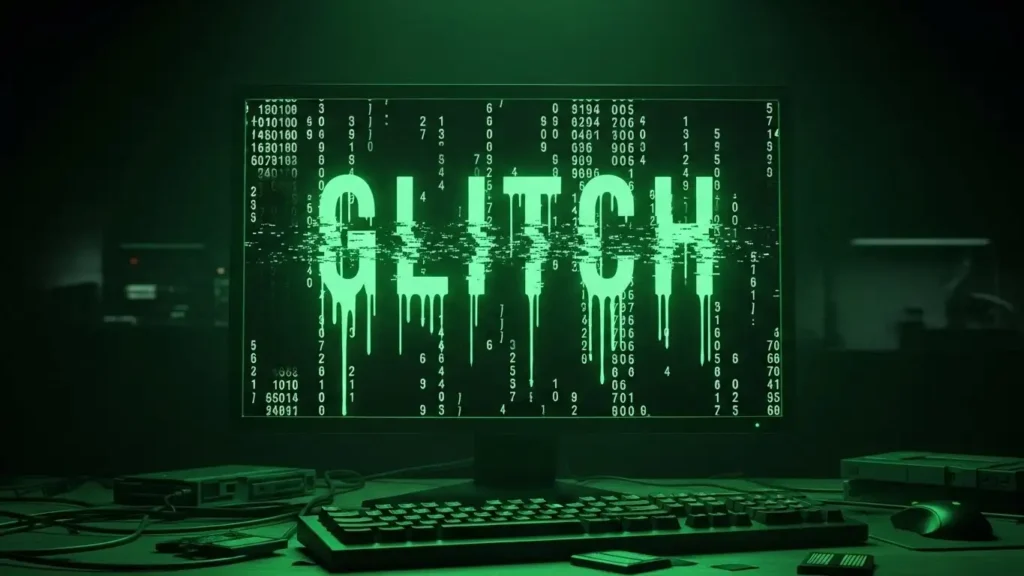
Ein Glitch Text Generator ist das mächtigste Werkzeug, um gewöhnliche Nachrichten in chaotische, visuell verstörende Kunstwerke zu verwandeln, die sofort ins Auge fallen. Hast du dich jemals gefragt, wie andere Nutzer diese seltsamen, “kaputten” Buchstaben erzeugen, die so aussehen, als würde der Bildschirm schmelzen? Das ist kein Fehler in der Matrix. Das ist Absicht.
In der digitalen Welt kämpfen wir alle um Aufmerksamkeit. Ein normaler Text in Arial oder Helvetica geht in der Masse unter. Aber ein Text, der aussieht, als wäre er von einem digitalen Geist besessen? Der fällt auf.
In diesem Artikel zeige ich dir nicht nur, wie du diese Effekte erstellst, sondern erkläre auch die Technik dahinter und worauf du achten musst, damit deine Botschaft lesbar bleibt.
Was ist eigentlich Zalgo Text?
Bevor wir in die Praxis gehen, müssen wir verstehen, was wir hier eigentlich tun. Zalgo Text, oft auch als “Glitch Text” oder “Scary Text” bezeichnet, stammt ursprünglich aus der Internet-Kultur der frühen 2000er Jahre. Der Name bezieht sich auf eine Internet-Legende (Creepypasta) über eine Entität namens “Zalgo”, die Wahnsinn und Zerstörung bringt.
Visuell wird dies durch Text dargestellt, der über die normalen Zeilenabstände hinauswuchert. Es sieht aus, als würde der Text bluten oder zerfließen.
Die Technik: Kombinierende Unicode-Zeichen
Viele glauben, dass man für diesen Effekt programmieren können muss. Das stimmt nicht. Das Geheimnis liegt im Unicode.
Unicode ist der internationale Standard für Schriftzeichen auf Computern. Er enthält nicht nur Buchstaben wie A, B oder C, sondern auch sogenannte “kombinierende diakritische Zeichen”. In vielen Sprachen werden diese genutzt, um Akzente zu setzen (wie das é im Französischen oder das ü im Deutschen).
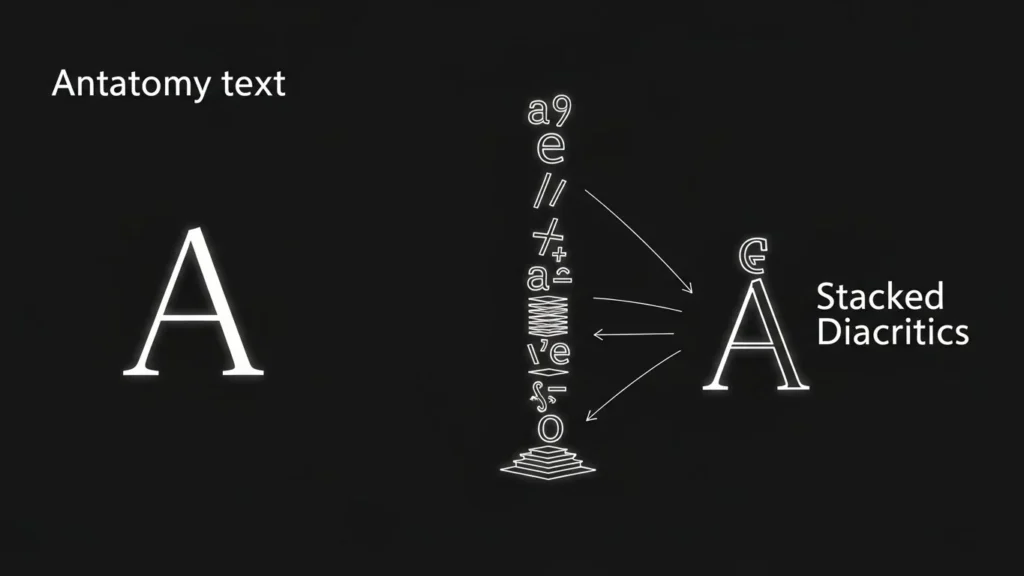
Der Trick beim Glitch-Effekt ist die Übertreibung. Ein Glitch Text Generator stapelt diese diakritischen Zeichen dutzendfach über, unter und in die Mitte eines normalen Buchstabens.
- Normal: a
- Mit Akzent: ä
- Zalgo: à̸̓ͅl̶͇̋l̵̼͘ë̶̮́s̶̹̏ ̵̟͝k̵͕͝à̸̓ͅp̶̹̏ù̸̓ͅt̶̹̏t̶̹̏
Das System versucht, alle diese Markierungen auf einem einzigen Platz darzustellen, was zu dem typischen, überladenen Chaos führt.
Wie unser Glitch Text Generator funktioniert
Die Bedienung ist denkbar einfach, aber das Ergebnis ist komplex. Du musst keine Codes auswendig lernen. Ein modernes Tool übernimmt die schwere Arbeit für dich. Hier ist der Prozess Schritt für Schritt:
- Eingabe: Du schreibst deinen Satz (z.B. “Hallo Welt”).
- Verarbeitung: Das Tool zerlegt jeden Buchstaben und weist ihm eine definierte Anzahl an Störungen zu.
- Adjustierung: Du kannst oft einstellen, wie stark der Effekt sein soll. Ein bisschen “Rauschen” für subtile Ästhetik oder komplettes Chaos für den Horror-Faktor.
- Kopieren: Das Ergebnis wird als normaler Text behandelt. Du kannst ihn einfach kopieren und fast überall einfügen.
Wo kannst du Glitch-Schriften verwenden?
Nicht jede Plattform geht gleich mit diesen Zeichen um. Da Zalgo-Text vertikal viel Platz einnimmt, kann er Layouts zerschießen. Doch genau das ist oft das Ziel. Hier sind die besten Einsatzgebiete:
1. Social Media Bios und Kommentare
Auf Instagram oder TikTok ist der Platz in der Bio begrenzt. Ein einziges Wort im Glitch-Stil kann mehr über deine Persönlichkeit aussagen als zehn Emojis. Es signalisiert: “Ich bin anders, vielleicht ein bisschen edgy oder tech-affin.”
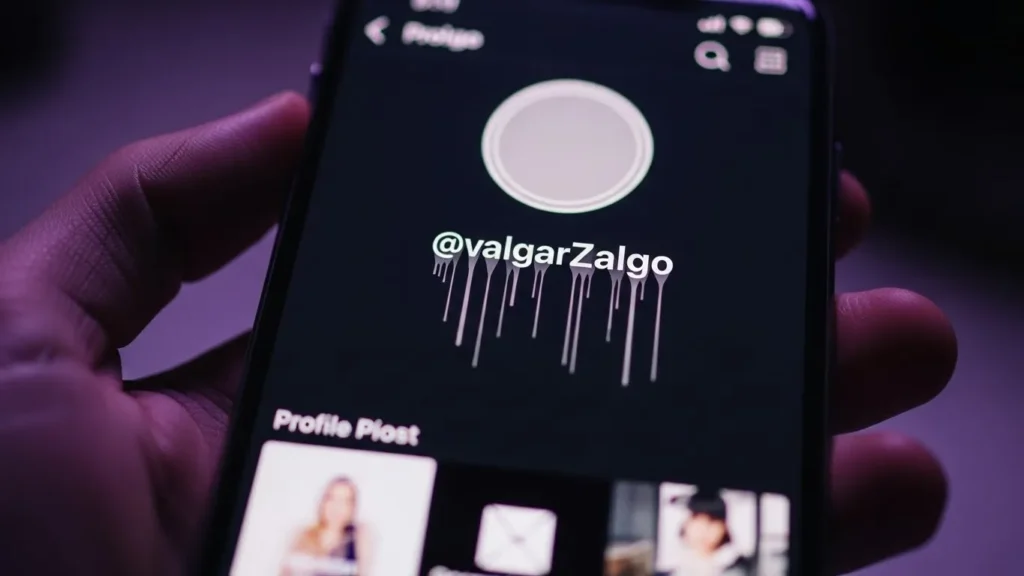
2. Gaming Profile (Roblox, Steam, Minecraft)
3. Discord und Chat-Apps
Discord ist ein Paradies für Text-Formatierungen. Du kannst Glitch-Text nutzen, um Ankündigungen hervorzuheben oder um auf Servern eine gruselige Atmosphäre für Halloween-Events zu schaffen. Allerdings gibt es hier Tricks zur besseren Lesbarkeit. Mehr dazu lernst du in unserer Anleitung Discord Text formatieren.
4. Kreative Projekte & Webdesign
Webdesigner nutzen diesen Effekt oft für “404 Fehlerseiten” oder für Überschriften in Cyberpunk-Designs. Es bricht das sterile Raster des Internets auf.
Wichtiger Hinweis: W3C Web Accessibility Initiative und andere Experten bestätigen immer wieder, dass übermäßiger Gebrauch von Unicode-Hacks die Barrierefreiheit einschränkt. Screenreader (Vorleseprogramme für Blinde) können Zalgo-Text nicht entziffern. Nutze diesen Effekt also sparsam und niemals für lebenswichtige Informationen.
Denke aber immer an die Dosierung. Wie bei einem starken Gewürz wirkt der Effekt am besten, wenn er gezielt eingesetzt wird und nicht das ganze Gericht überdeckt. Die Balance zwischen Lesbarkeit und Ästhetik ist der Schlüssel.